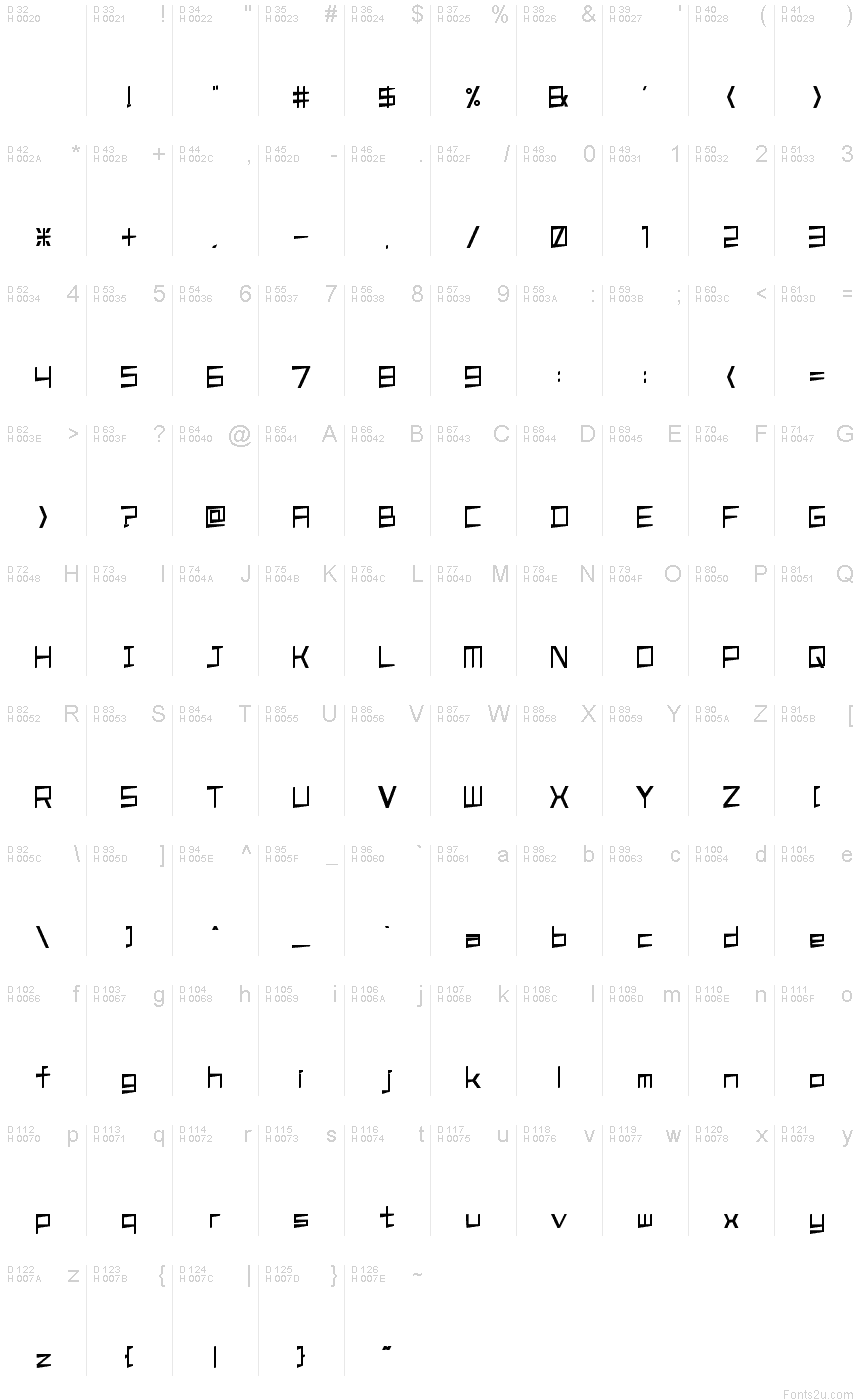
S A50kmh, autorstwa Kato Masashiego z Flop Design, to darmowy, kanciasty technokrój typu display, który nawiązuje do szybkości znaków drogowych i ma oszczędny, modułowy rytm. Litery opierają się na szerokich, płaskich pociągnięciach i ostrych przekątnych cięciach, nadając krojowi mechaniczny, napędzany prędkością charakter, który bardziej przypomina panele wskaźników i naklejki tuningowe niż neutralne, geometryczne pismo.
Świetnie sprawdzi się w nagłówkach plakatów, ekranach tytułowych gier, w brandingu sportów motorowych, ulotkach klubowych i wszystkich projektach, w których liczy się dynamika. Jako darmowy font, sprawdzi się również w krótkich logotypach, planszach tytułowych i monogramach, ponieważ kwadratowe kształty i ścięte otwory sprawiają, że nawet krótkie słowa wyglądają szybko i precyzyjnie zaprojektowane.